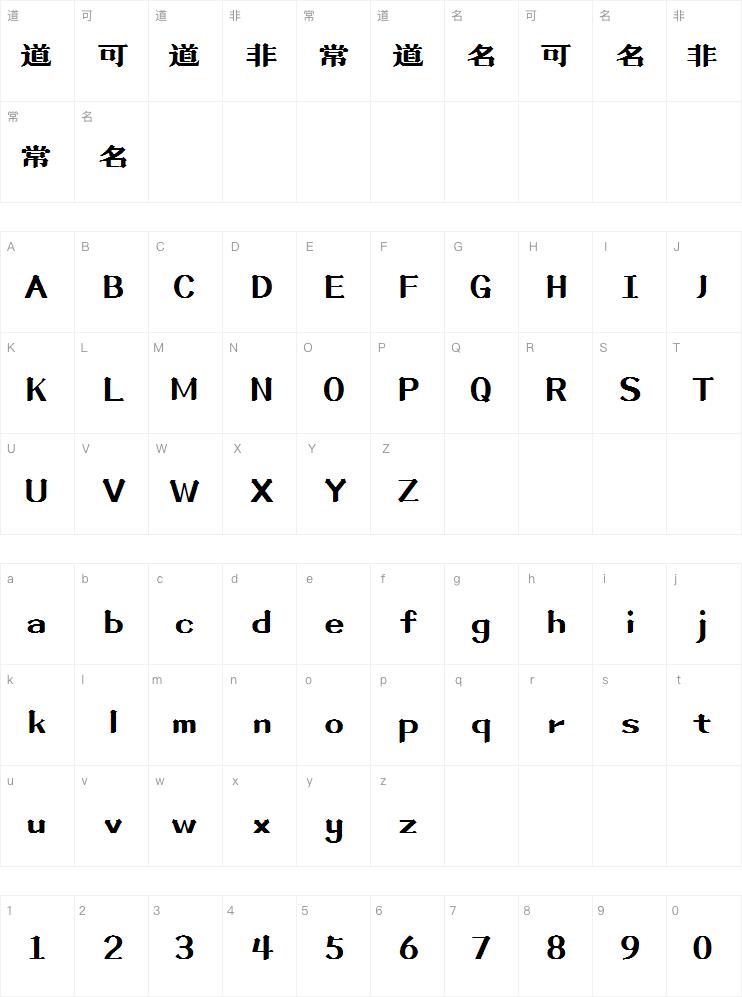
上首标题宋体,简体中文约6763字,在保留传统宋体“横细竖粗、饰角明显”的结构基因基础上,进行了重创造性突破。横竖笔划增加了突出的尖角、具有轻奢、文艺。字体风格稳重呈方块形,整体特征坚硬、有力。具有现代、国际化的指向性字形紧凑,但不失美感。刚正而不失稳重,横竖笔画加人了尖突的效果,让字形更显英朗气质。突出个性,端庄秀美。